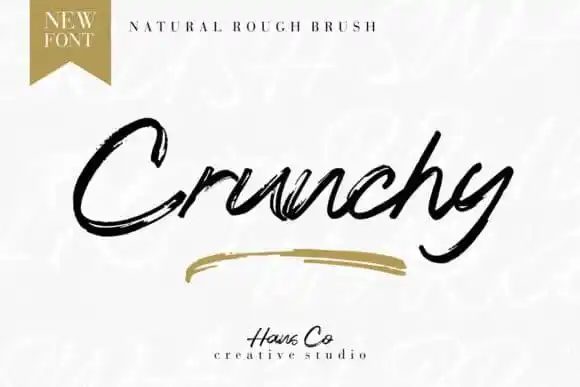
Crunchy Brush Font – Download Grátis
Descubra a beleza única de Crunchy Brush Font, uma elegante fuente brush que traz estilo moderno ao seu design. Com sua estilo artesanal e natural, essa fuente oferece um toque sofisticado e encantador aos seus projetos. Ela foi criada pelo font designer HansCo. Este é perfeito para criar logotipos, estilizar marcas de produto, criar postagem em redes sociais, ou qualquer outra necessidade que seu projeto possa exigir. Com a Crunchy Brush Font na sua coleção, você pode liberar a criatividade e transformar seus projetos digitais em verdadeiras obras de arte. Sua simplicidade única faz com que ela seja uma opção ideal para qualquer aplicação gráfica. Descubra como essa fuente pode revolucionar a aparência dos seus materiais e faça você ser notado entre o resto. Instale-a agora e inicie sua jornada criativa.